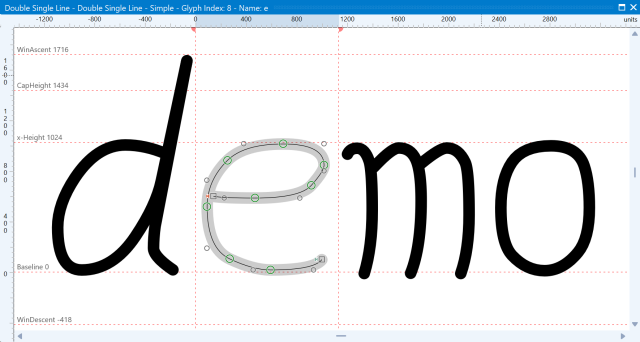
學習如何使用 FontCreator 設計用於切割、雕刻與 CNC 應用的單線字體。本指南涵蓋了為這些工具優化的開放輪廓字形的創建方式。
單線字體對於切割、雕刻和 CNC 應用程式至關重要。Make The Cut、Sure Cuts a Lot、Rhino、Silhouette Studio 和 Cricut Design Space 等程式支援使用字體在各種材料上切割設計。儘管 OpenType 字體通常基於閉合輪廓,使得真正的單線 OpenType 字體不存在。然而,FontCreator 提供了允許您設計開放輪廓的工具,從而能夠創建適用於這些任務的字體。
要創建單線字體,您需要啓用 FontCreator 的 開放輪廓 功能。方法如下:
啓用單筆劃模式:
轉到 字體導出設置 對話框,並將 開放輪廓 設置為 單筆劃 或 雙筆劃。單筆劃更高效,但雙筆劃可能更適合某些雕刻軟件。測試兩者以查看哪種最適合您的設置。
啓用後,輪廓將不再被填充,而是顯示為筆劃,這有助於設計單線字體。
創建新字體:
首先在 FontCreator 中創建一個新字體。在字形編輯器中,選擇一個字形並使用 繪圖工具 設計開放輪廓。並非所有輪廓都需要開放——像 'O' 這樣的字形可能仍需要閉合輪廓。
插入和編輯輪廓:
使用插入菜單中的 插入輪廓 功能添加新輪廓。對於直線,在添加點時按住 Shift 鍵。可以通過拖動鼠標創建曲線。要打開現有的閉合輪廓,右鍵單擊輪廓並選擇 切換開放輪廓。
完成字體後,將其導出為 .ttf 文件。測試 單筆劃 和 雙筆劃 導出選項,以確定哪種最適合您的項目。